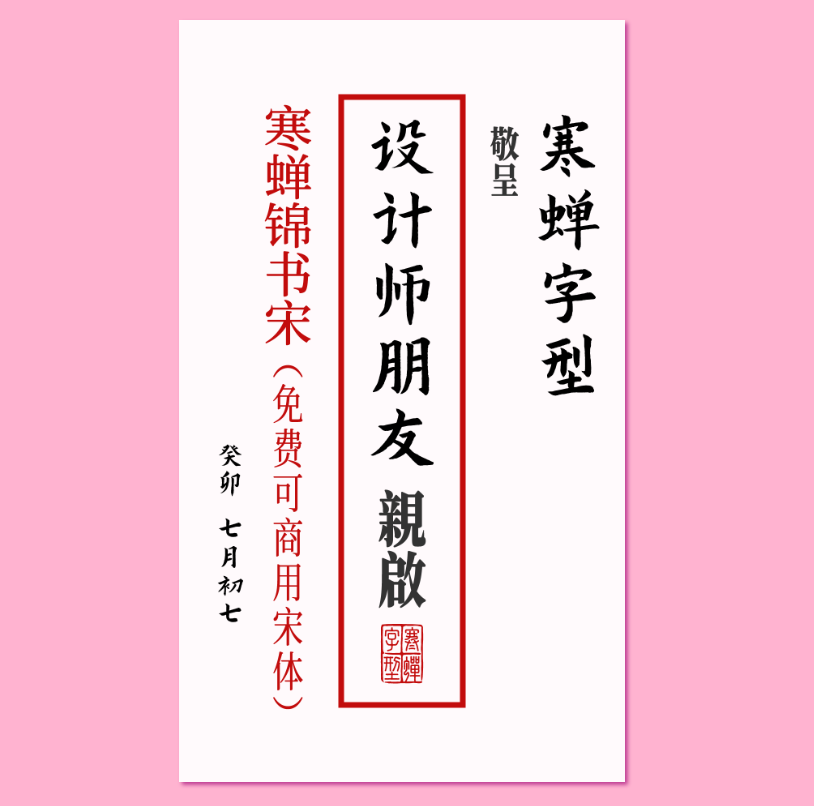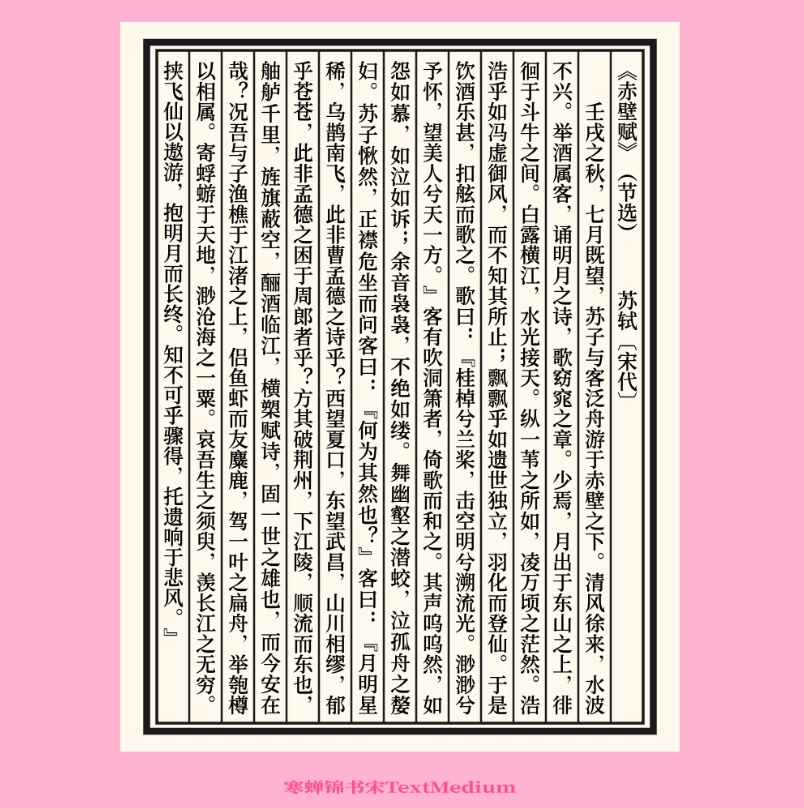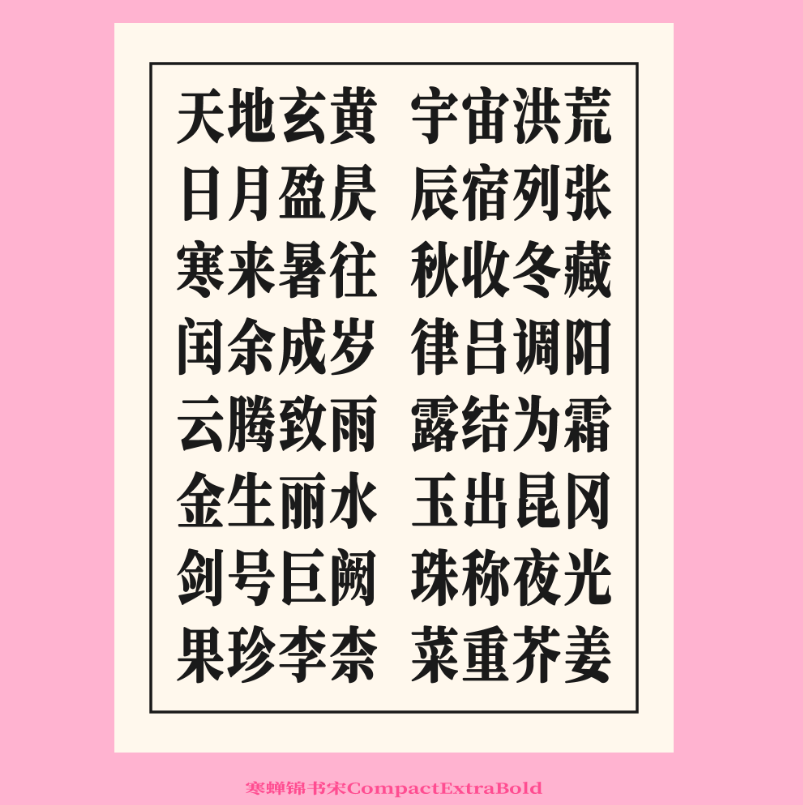
寒蝉锦书宋 (Chill Jinshu Song) 是一款基于思源宋体修改而来的免费可商用宋体字体。作者在保留宋体结构的基础上,对所有字的笔画末端进行了圆角处理,使字体更加柔和温润,阅读起来更加舒适。同时对字重比例也进行了重新构建,调整字体粗细比例和优化字间距与行间距,使其更均衡,排版更美观。
寒蝉锦书宋的 5 个字重(按粗细从浅到深)分别是:Light(细)、Regular(常规)、Medium(中等)、Bold(粗)、Heavy(特粗)。丰富的字符集,包含 GB/T 2312、通用规范汉字、BIG5、GBK 等字符集,中文字符量达 29836 个,总字符量(Unicode 17.0)为 45622 个,可以适配海报设计、包装设计、书籍排版等多种不同排版与设计场景。
- 寒蝉锦书宋GBK2.0版本:5 字重,增加 3 窄体和 2 宽体以及 2 阅读用字,字符集数量共 30844,支持 GB18030-2022 实现级别 2 。
- 寒蝉锦书宋PRO2.0版本:1 字重,增加 soft 和斜体,字符集数量共 45622,支持 GB18030-2022 实现级别 2 。